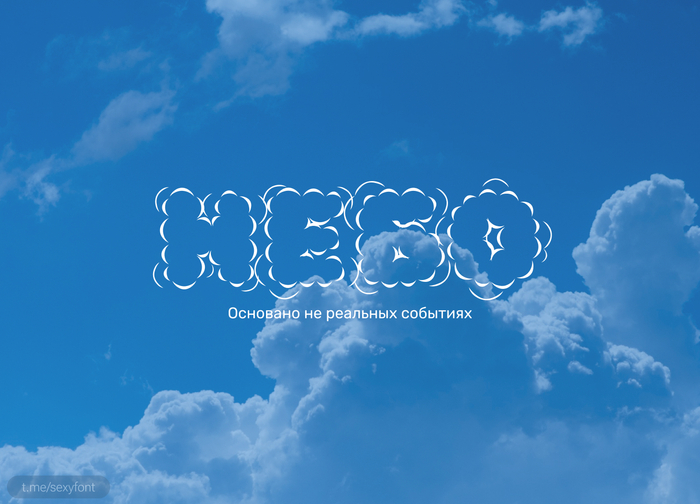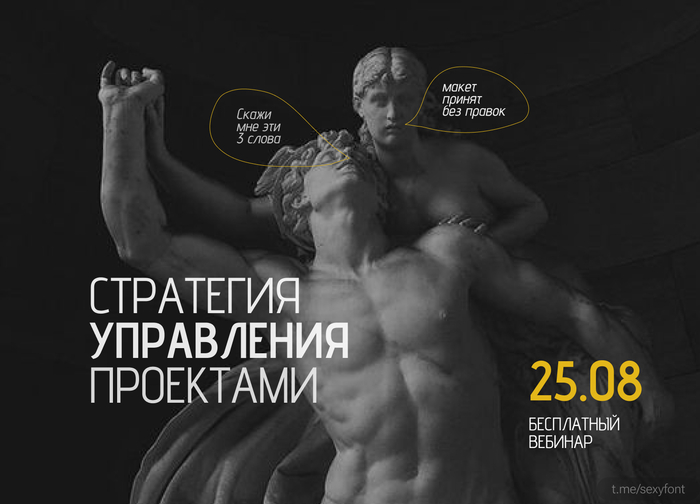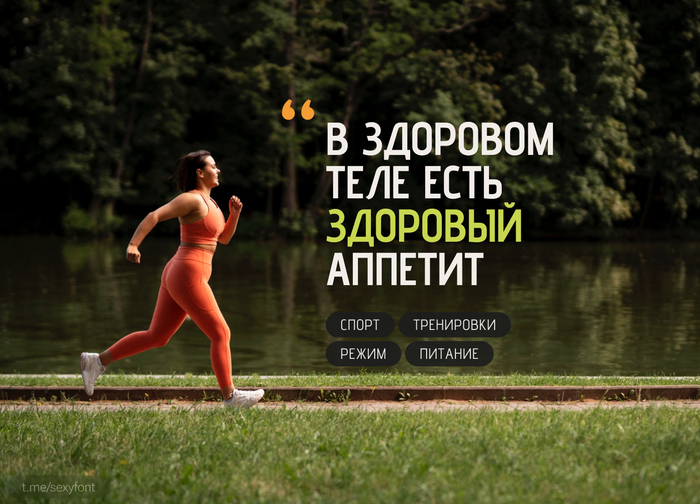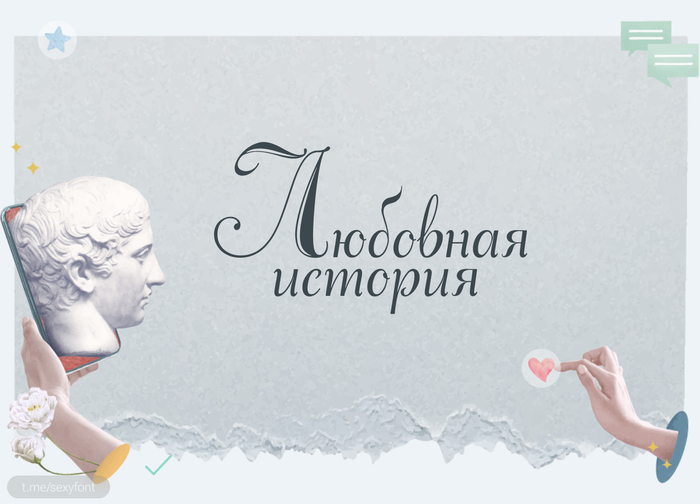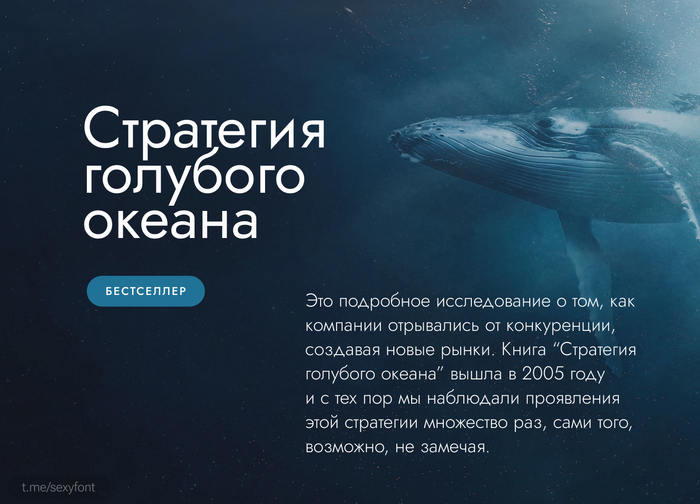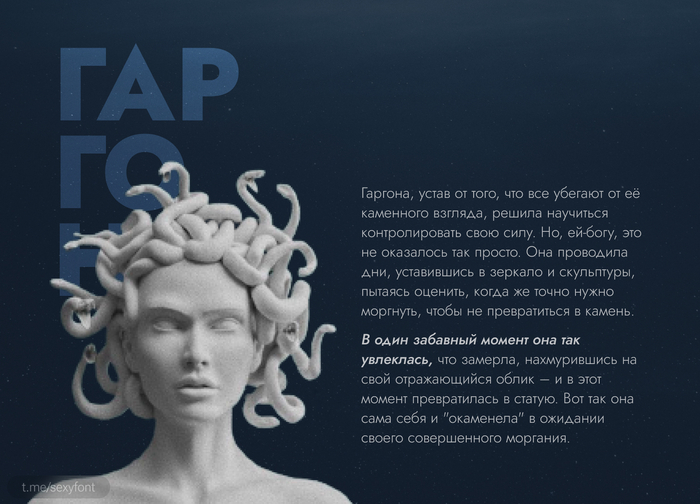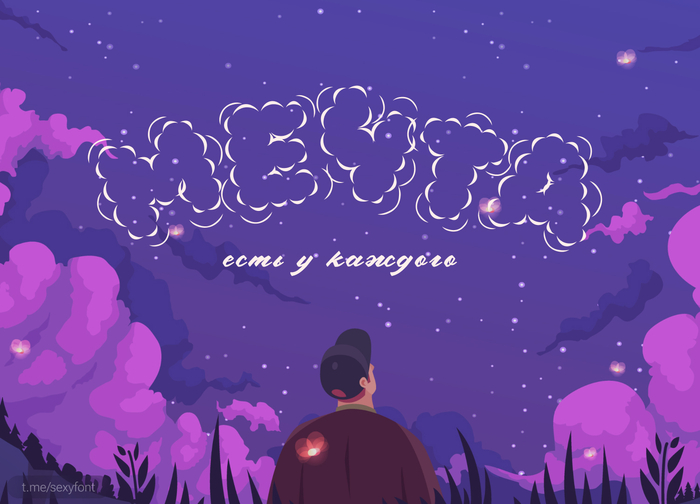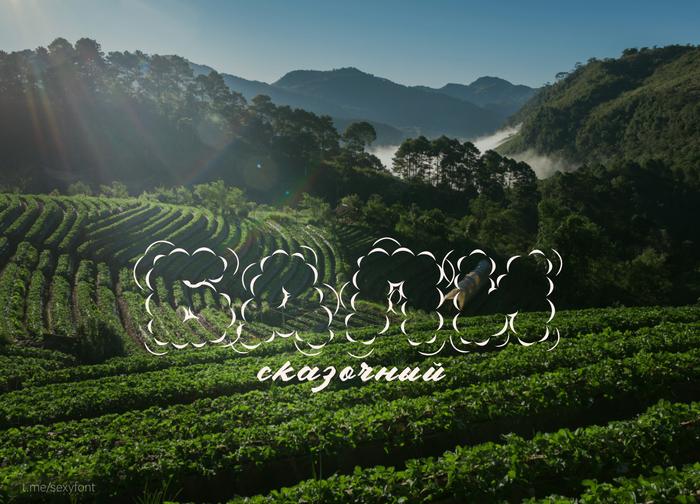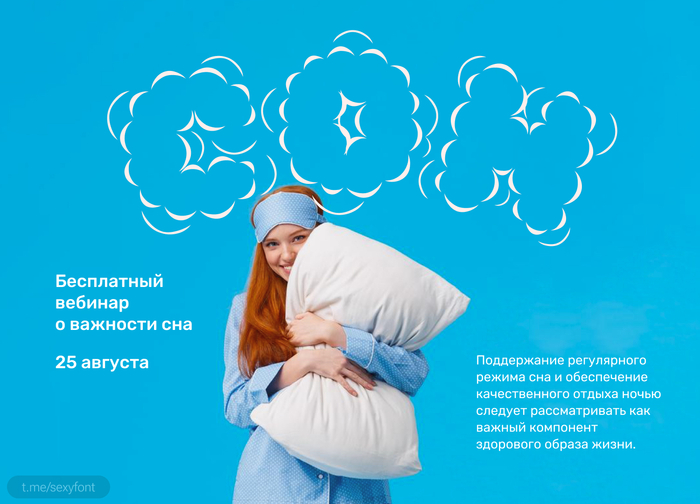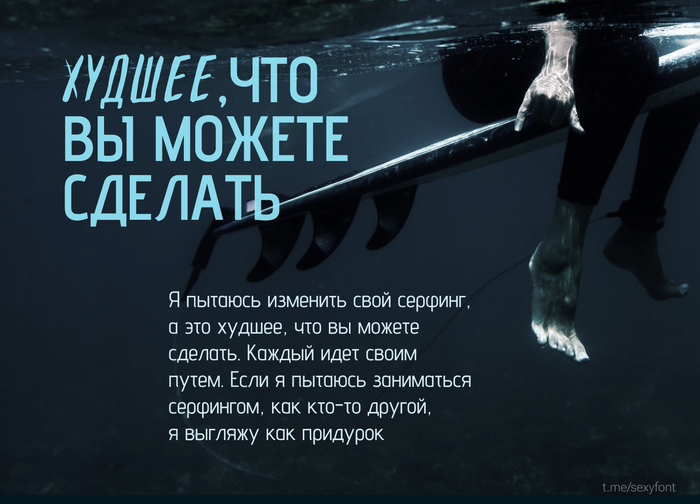
Шрифт bergamasco
Шрифт bergamasco. Акцидентния контрастная антиква. Бесплатно для личного и коммерческого использования. Чего тут рассказывать) Смотри презентацию.
Шрифт Jost. Кириллица
Хорошо читаемый, кириллический шрифт с google Font. Подойдет не только для заголовков, но и объемных абзацев. Так же радует большое количество начертаний и вариативность. От тонкого до жирного.
Шрифт "Осенний свитер"
ps. Хороним букву "Т" ?)
Шрифт Adana script
Давно не было рукописных. Это кириллизация от А.Л. Гофманн в свойственном ей стиле. Заглавные буквы выглядят конечно странновато)
Шрифт Akony. Бесплатный. Кириллица
Akony. Не так часто встретишь хороший, размашистый шрифт. Подойдет для коротких заголовков. У меня как обычно ассоциации с космосом. В презентации показал. Но в целом зайдет и под бизнес и под ИТ, авто и т.п
Бесплатный шрифт Advent pro
Читаемый кириллический шрифт. Вполне подойдет для абзацев. Есть спорные решения в некоторых буквах. Но для разнообразия почему бы и да. Радует, что шрифт вариативный и можно настроить ширину и толщину символов.
Шрифт Rubik puddles. Кириллица
Сделал презентацию очень нестандартного шрифта. Использовать стоит крайне аккуратно) желательно в коротких словах и на однородном фоне. Либо как декоративный элемент. Иначе хрен разберёшь.